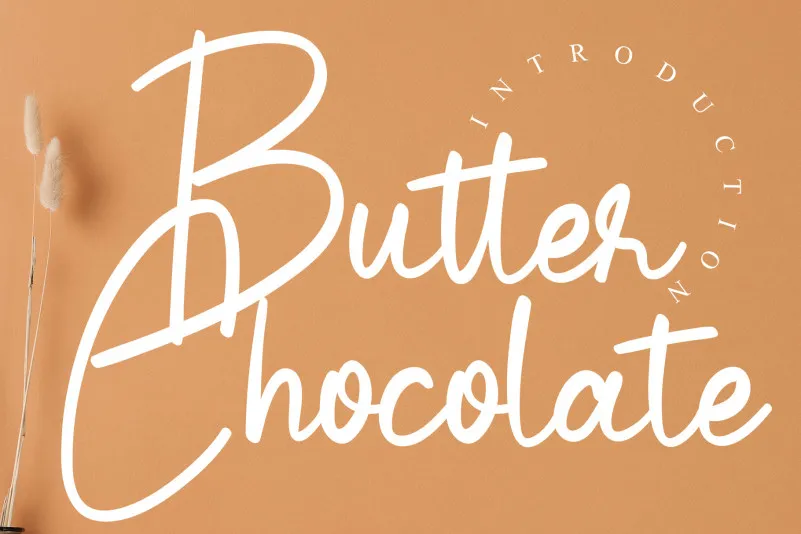
A fonte ‘Butter Chocolate Script Font’ é uma escolha perfeita para quem busca algo que seja único e singular. Criada pelo designer creativeletter, ela oferece uma experiência visual maravilhosa e encantadora que se destaca por sua elegância delicada e suave textura. Inspirada na melancolia do chocolate bem amargado, mas ainda assim repleta de um toque irresistivelmente saboroso, essa fonte escrita a mão exala uma sensação única de conforto e calma, ideal para usar em projetos que valorizam a criatividade e o design delicado. Ideal tanto para criações digitais quanto impressas, essa font se destaca como um recurso gráfico notável, tornando-a uma escolha certeira para aqueles buscando personalizar seus materiais de forma única e sofisticada.